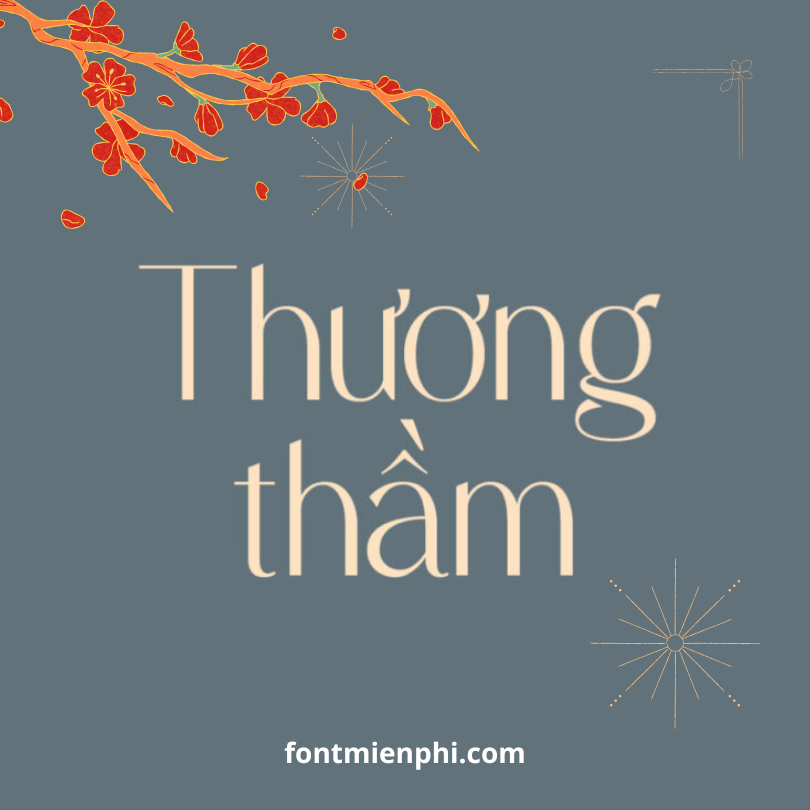
Font Việt hóa 1FTV VIP Magiesta
Font Việt Hóa 1FTV VIP Magiesta – Sự Kết Hợp Độc Đáo Giữa Thanh Lịch & Cá Tính
1. Tổng Quan
1FTV VIP Magiesta là một trong những font chữ Việt hóa cao cấp thuộc bộ sưu tập độc quyền của 1FirstFont (1FTV), mang đậm phong cách hiện đại, phá cách nhưng vẫn giữ nét thanh lịch. Với thiết kế độc đáo, Magiesta trở thành lựa chọn hoàn hảo cho các dự án đòi hỏi sự sáng tạo và khác biệt.
2. Đặc Điểm Nổi Bật
✔ Việt hóa hoàn chỉnh: Hỗ trợ đầy đủ bảng mã Unicode, bao gồm tất cả các ký tự tiếng Việt có dấu, đảm bảo hiển thị sắc nét trên mọi nền tảng.
✔ Phong cách độc đáo: Magiesta sở hữu nét chữ mềm mại kết hợp với những đường nét phá cách, tạo điểm nhấn ấn tượng cho mọi thiết kế.
✔ Bản VIP cao cấp: Được thiết kế với độ phân giải cao, không bị vỡ nét khi in ấn hoặc phóng to, đảm bảo chất lượng hình ảnh sắc nét trong mọi trường hợp.
3. Ứng Dụng Đa Dạng
• Thiết kế thương hiệu: Logo, namecard, bao bì sản phẩm.
• Truyền thông & Marketing: Banner, poster, standee, brochure.
• Digital Content: Website, social media, video intro.
• Ấn phẩm nghệ thuật: Tạp chí, bìa sách, thiệp mời.
• Kết hợp với các font sans-serif như Montserrat, Helvetica để tạo sự cân bằng trong thiết kế.